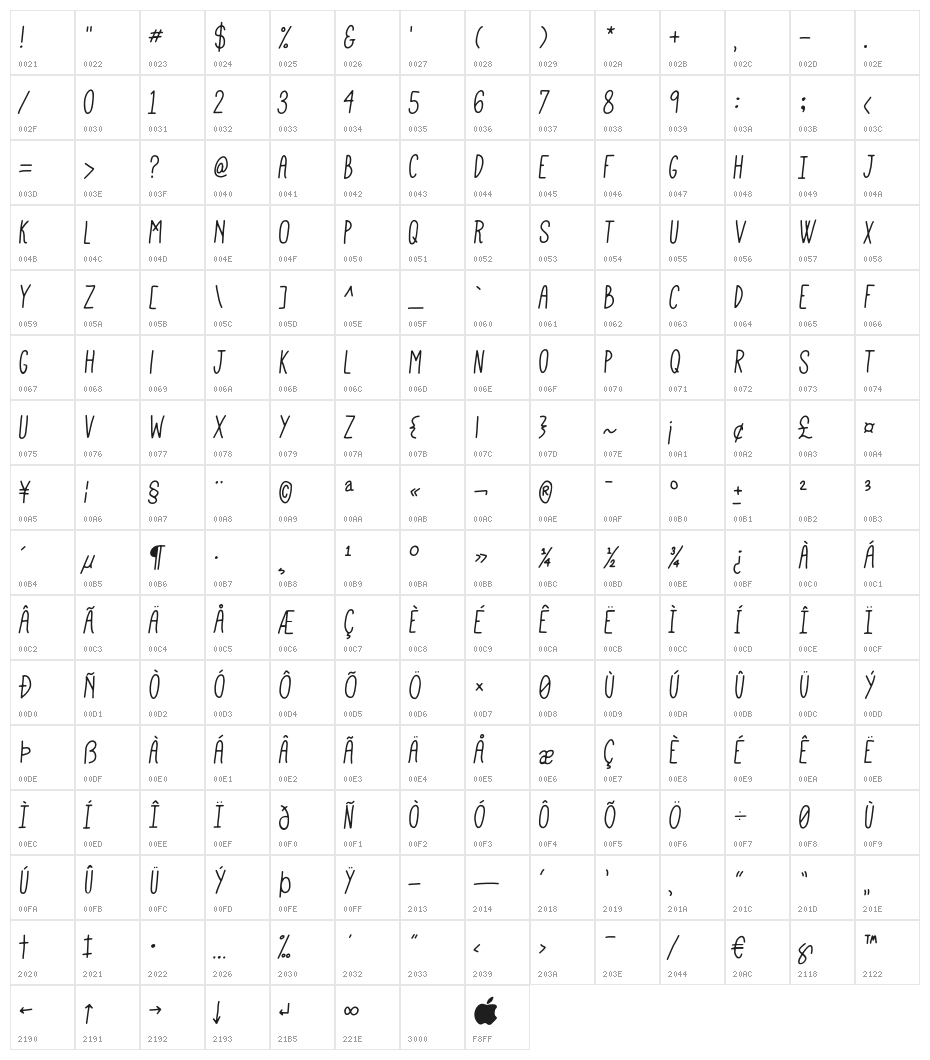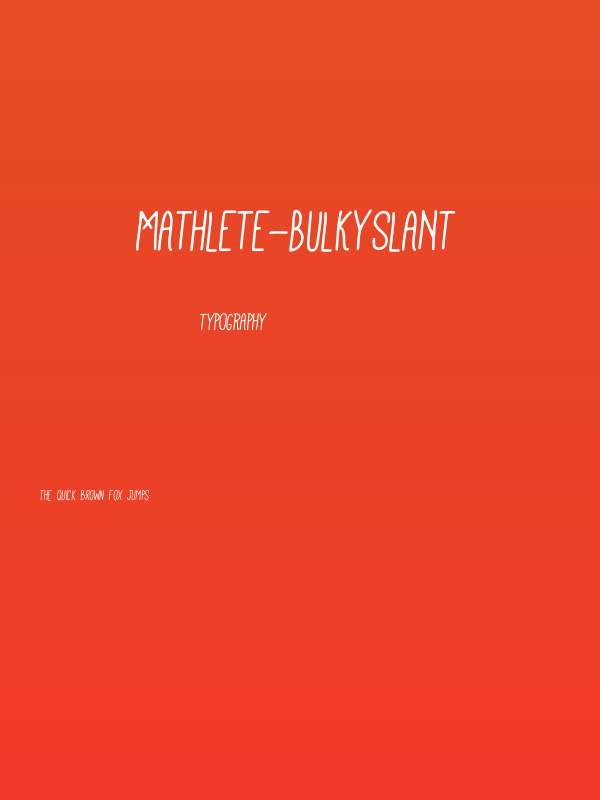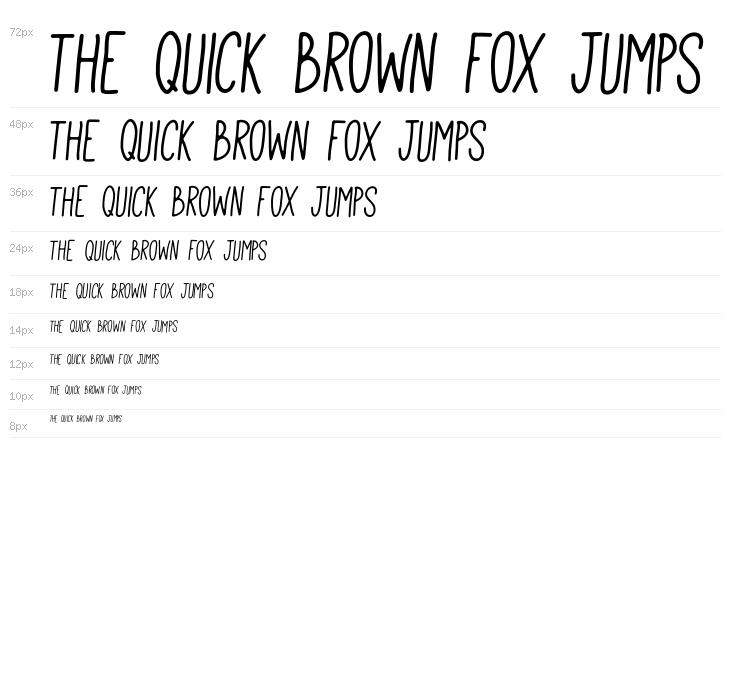
Mathlete-BulkySlant Font
| Gesamtstil | Playful, Informal |
| Anwendungsfall | Headlines, Logos, Informal Text |
| Vorgeschlagene Projekte | Ideal for children's books, playful branding, event invitations, and casual social media graphics. |